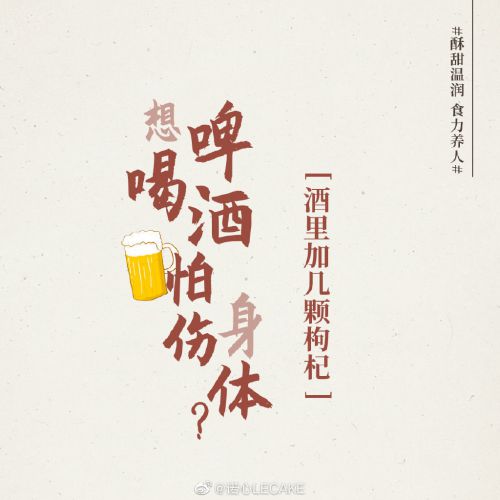
庞门正道粗书体
字库品牌: 庞门正道
庞门正道粗书体是一款由庞门正道推出的中国风手写体字体,以古典手写风与豪放气韵为核心设计亮点。 庞门正道粗书体的结构方正大气,重心居中稳固,中宫宽博的设计让字体兼具稳重感与舒展性,视觉上平衡且富有张力。其笔画融入手写笔触的自然韵味,起笔与收笔处点缀细腻的顿笔装饰元素,既保留手写的灵动,又通过方头笔画端部强化力量感,尽显传统书法的豪放气质。 作为“粗书体”,字重饱满却不失层次,粗细对比适中的处理让字体在视觉上主次分明。笔画多以断开状态呈现,巧妙还原手写过程中的自然断连,避免机械感,让每一笔都透着随性与生动。 无论是古典主题海报、文化宣传物料,还是书法风格标题设计,庞门正道粗书体都能精准传递中国风的古典底蕴与手写的温度。更值得关注的是,这款字体支持免费商用,为设计师提供兼具美感、实用性与版权保障的创作工具。